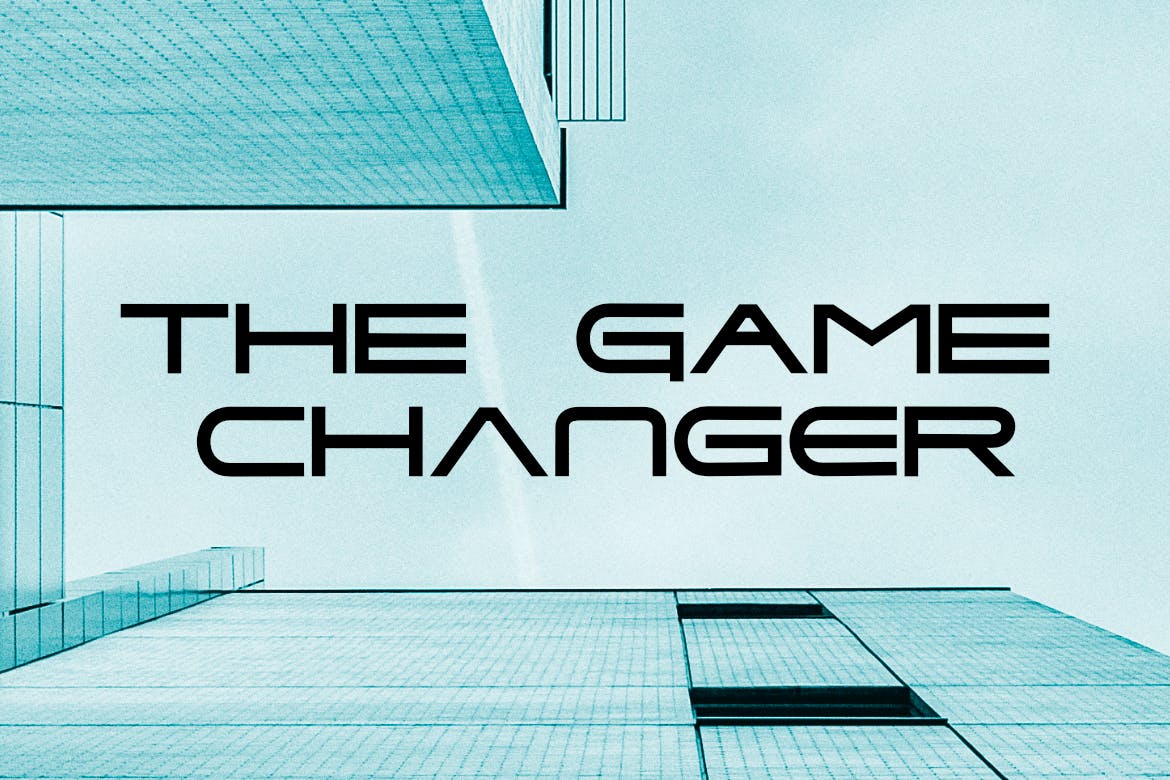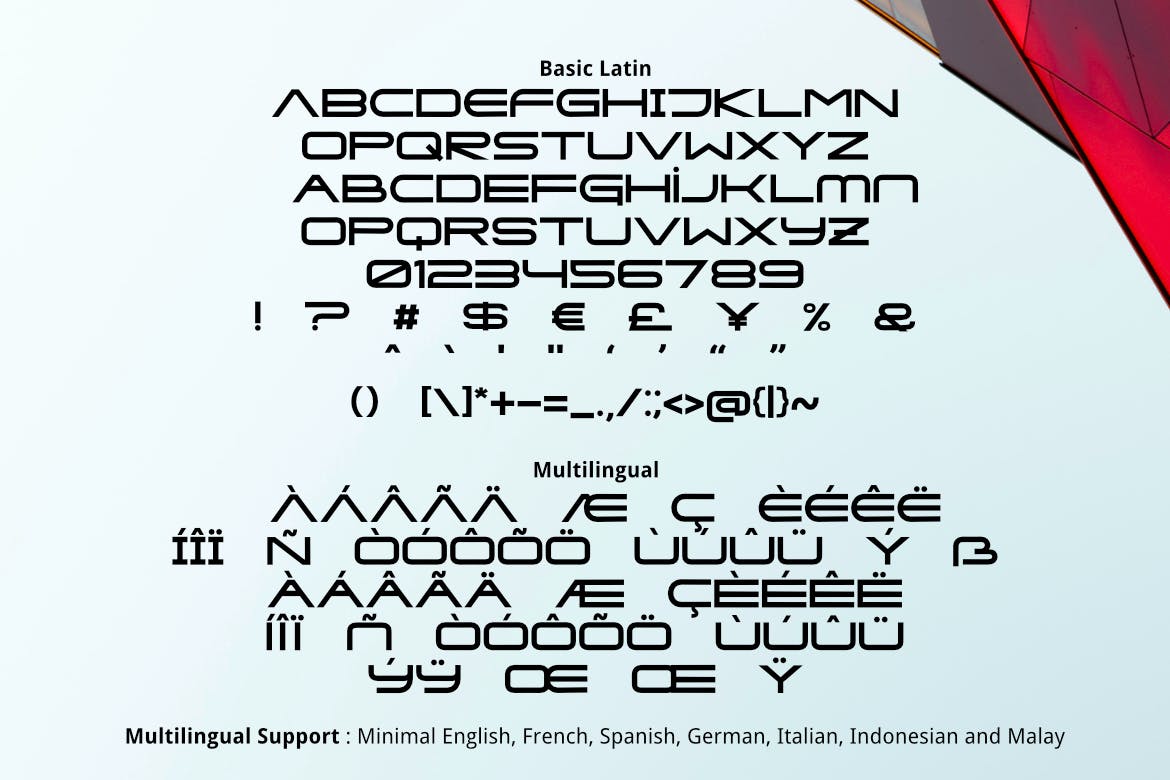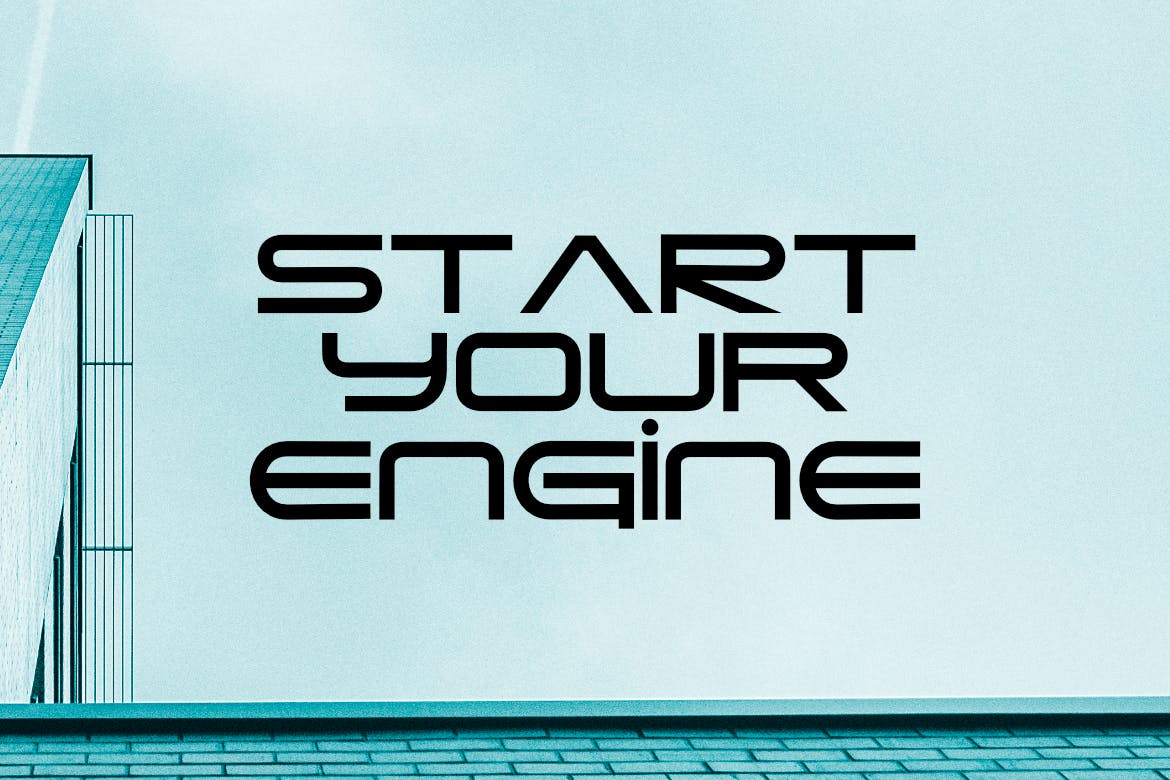
فونت Cemen
فونت Cemen یک فونت چندمنظوره و مدرن است که برای پروژههای مختلفی مانند کتابهای کودک، نقلقولها، لوگوها، سرفصلها و عناوین مناسب میباشد.
پشتیبانی از کاراکترهای پایه لاتین (حروف، اعداد و نمادهای استاندارد انگلیسی) و پشتیبانی چند زبانه (حداقل انگلیسی، فرانسوی، اسپانیایی، آلمانی، ایتالیایی، اندونزیایی، مالایی)